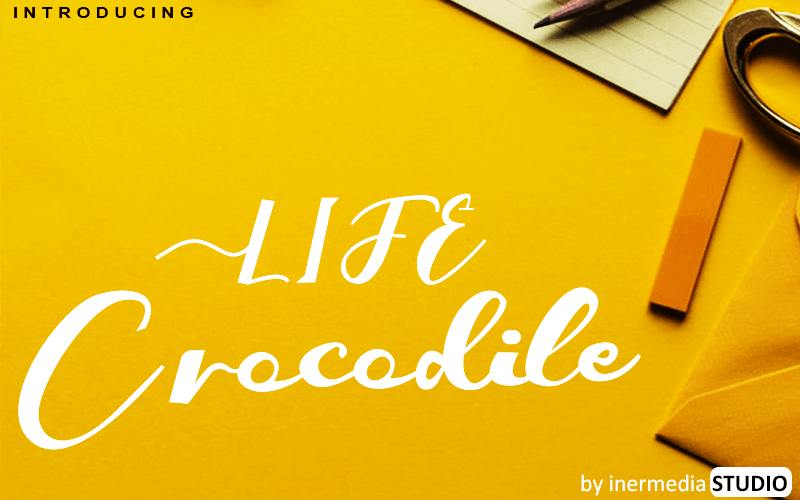
Crocodile Script Font – Download Grátis
A Crocodile Script Font é uma excelente opção para quem busca uma fonte escrita à mão que mantém suas influências classicamente calligráficas ao mesmo tempo em que se destaca por sua modernidade e frescura inovadora. Esta fonte tem um poder de adaptação significativo, o que a torna perfeita para várias ideias criativas. Ela é adequada tanto para letras de cartão de visita e títulos quanto para material de estaçãoaria. Este tipo de fonte não apenas oferece uma variação em diversos usos, mas também adiciona um toque sofisticado e contemporâneo a qualquer projeto gráfico. A Crocodile Script Font é uma escolha ideal para designers que valorizam tanto o estilo clássico quanto as características atuais do design moderno.